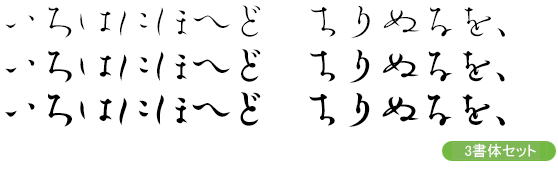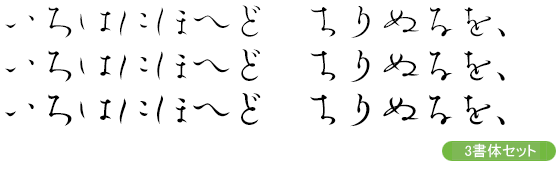
手書き風書体
清流かな-B
SeiryuKana-B
草書の走り書きの妙とも言うべき流麗さに、明朝の要素を加味して作り上げています。オールドなイメージを残しつつも、その概念にとらわれず大仮名に設計してあるので、近代的な組版にも対応するマルチな性格を備えています。ボディの不揃いさはRENFONTの中でも最大級ですが、その分、心地よいゆらぎの効果は抜群です。その名のごとく清らかな水の流れのような、美しく味わい深い書体です。お得な5ウェイトセットもあります。